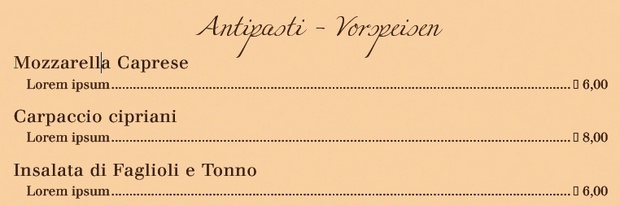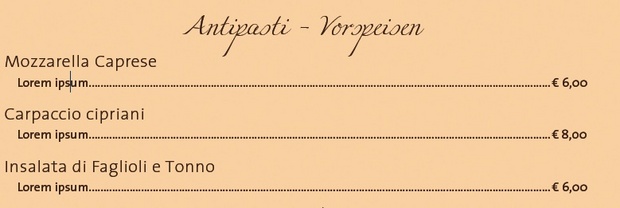
Passende Fließtextschrift zur Miama gesucht
Ich muss grad für einen bekannten von mir, der ein italienisches Ristorante besitzt eine möglichst günstige Take-Away Karte "designen". Alles schön und gut, wenn da mal nicht die festen Vorstellungen seinerseits wären ;)
Er hat ein schlichtes Schriftlogo im typischen Stile eines italienischen Ladens und möchte unbedingt die Miama haben, unter anderem natürlich auch, weil sie kostenlos ist. Und nun kommen wir zu meinem Problem:
Welche Schrift passt denn als Ergänzung zur Miama auf eine "Speisekarte"? Habt ihr da eventuell Ideen oder Vorschläge? Kostenlose Schriften wären natürlich am Besten (da er auch gerade erst beginnt), aber sofern dies nicht möglich ist, bin ich für alle Vorschläge offen.
So rein optisch bin ich ja der Meinung, dass nur eine Sans-Serif Schrift in Frage kommt, aber ich bin da ja leider nicht vom Fach und somit benötige ich bitte dringend Eure Hilfe.
willkommen im Forum :huhu: Zeigst Du uns mal ein Bild von der Miama?
Dann können wir uns viel besser vorstellen, was dazu passen könnte.
Meine bisherige Gedanken laufen in diese Richtung:
Optima *duck*
Helvetica :/
TheSans in Light (ich find die einfach unglaublich schön und mein Bild stört es nicht, aber ich bin eben auch ein Laie ;) )
Soweit meine Vorstellungen. Was haltet Ihr denn davon? Ist es arg amateurhaft oder durchaus ein brauchbare Variante dabei? :)
Muß es denn eine Grotesk sein? Hast Du schon mal über eine Klassizistische nachgedacht? Die Schriftwahl hängt natürlich auch vom Anspruch des Ladens ab: Billig-Pizza oder Nobel-Italiener.
Ich bin für alles offen. Die Vorschläge sind eben so meine Gedankenspiele gewesen.Allerdings sollte die Schrift nicht allzu teuer sein, wie gesagt, er möchte es möglichst günstig und trotzdem top...(natürlich, so wie eigentlich jeder :D)
Und auch beim Anspruch sind wir wieder in einer Mischsituation... Es ist kein Nobelitaliener, bei der sich irgendwelche Girlies an "Promis" ranmachen, aber erst Recht kein Billig-Italiener. Preise sind schon gehoben, aber nicht abgehoben ;)
Ich würde daher eher nicht die Helvetica nehmen, sondern die The Sans bevorzugen – die ist etwas schmaler und eleganter als die Helvetica. Die Frutiger ist auch eine schöne neutrale Schrift die sich gut verarbeiten lässt, die könntest Du alternativ mal probieren. Ansonsten könnte ich mir – wie Pachulke vorschlägt – auch sehr gut eine Serifenschrift vorstellen.
Bezüglich der Helvetica bin ich mit deiner Aussage bestätigt. Ich kann es nicht beschreiben, aber irgendwas hat mich eben beim Draufblicken an der Kombi mit der Helvetica gestört. Die Frutiger find ich auch sehr schön, aber sie wirkt für mich in der Kombi irgendwie ...ich weiß auch nicht..Bei der Frutiger stört mich auch irgendwas am optischen Eindruck in der Verbindung mit der Miama. Wie gesagt, ich kann das nicht beschreiben, irgendwas stört für mich da den "optischen Fluss". :s
Danke schön, hab jetzt ein wenig mit der Größe gespielt, wirkt schon ein wenig besser, aber irgendwas fehlt ganz eindeutig oder ich sollte einfach mal ne Pause machen:)
Hat denn noch jemand andere Alternativen als den bisherigen Liebling TheSans? :-)